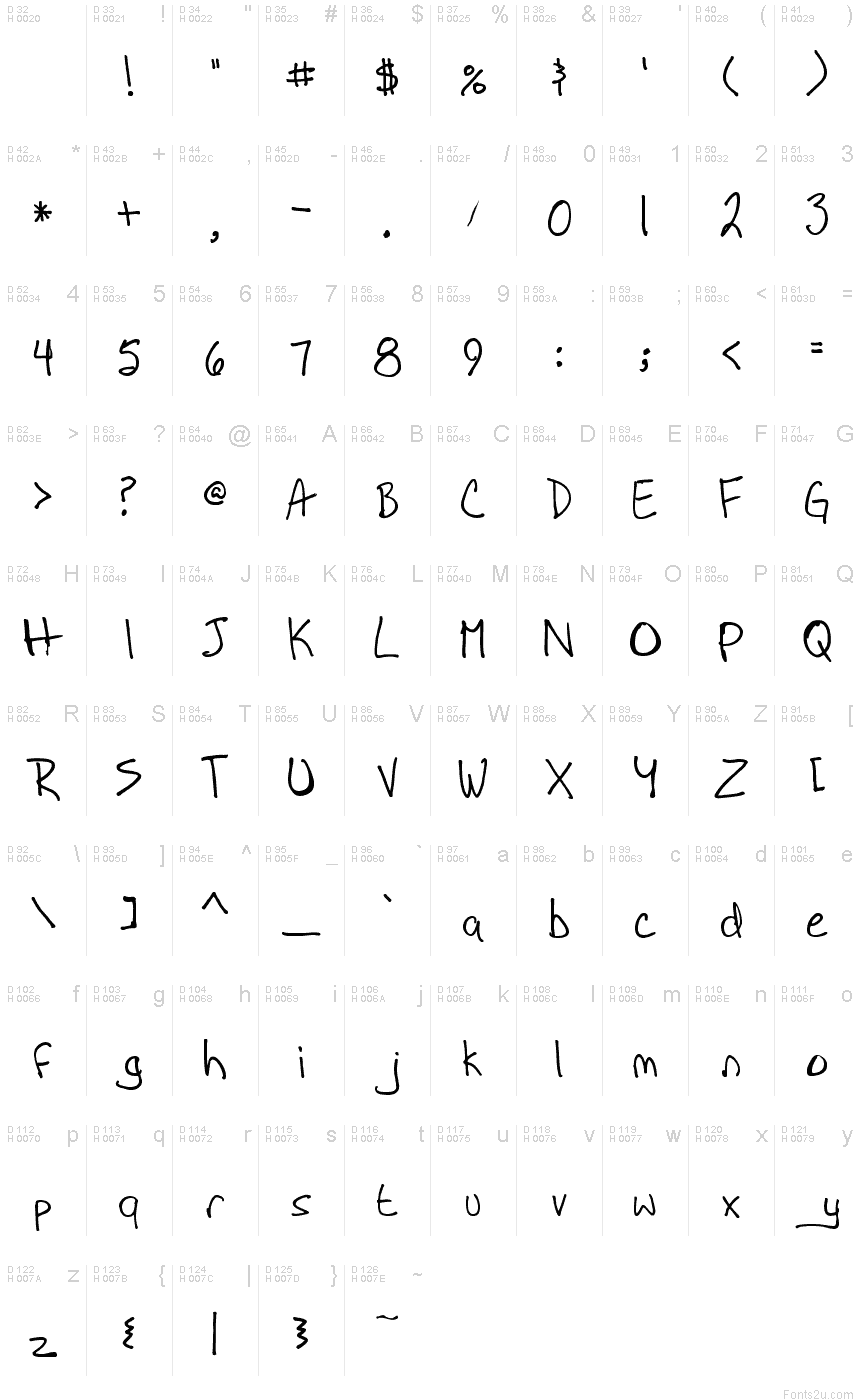
BoBsFrAnTiC True Type هو خط يدوي مجاني يبدو وكأنه خُطّ على عجل باستخدام قلم تحديد سميك. الحروف تتذبذب وتتعثر بين الأحرف الكبيرة والصغيرة، مما يمنح عائلة BoBsFrAnTiC إيقاعاً عصبياً متوتراً يبدو عفوياً بدلاً من أن يكون لطيفاً ومصطنعاً. السكتات غير متساوية ومشبعة بالحبر، مما يجعل النص يبدو خاماً، مفعماً بالطاقة، ومجنوناً بعض الشيء؛ إنه خيار رائع عندما تحتاج إلى خط يبدو وكأنه مكتوب باليد حقاً.
باستخدام BoBsFrAnTiC True Type، ستشعر أن عناوينك عبارة عن ملاحظات ممزقة من دفتر اسكتشات؛ إنه مثالي لمجلات الزين (Zines)، أغطية المذكرات، صور مصغرة على يوتيوب، ملصقات الفرق الموسيقية، الملصقات الجريئة، ومنشورات الهالوين. يتألق هذا الخط المجاني عندما يكون كبيراً وصاخباً؛ احتفظ بالنص الأساسي بخط بسيط بلا زوائد واترك BoBsFrAnTiC يتولى الأجزاء الجامحة والصاخبة.